Process Studio, 2019
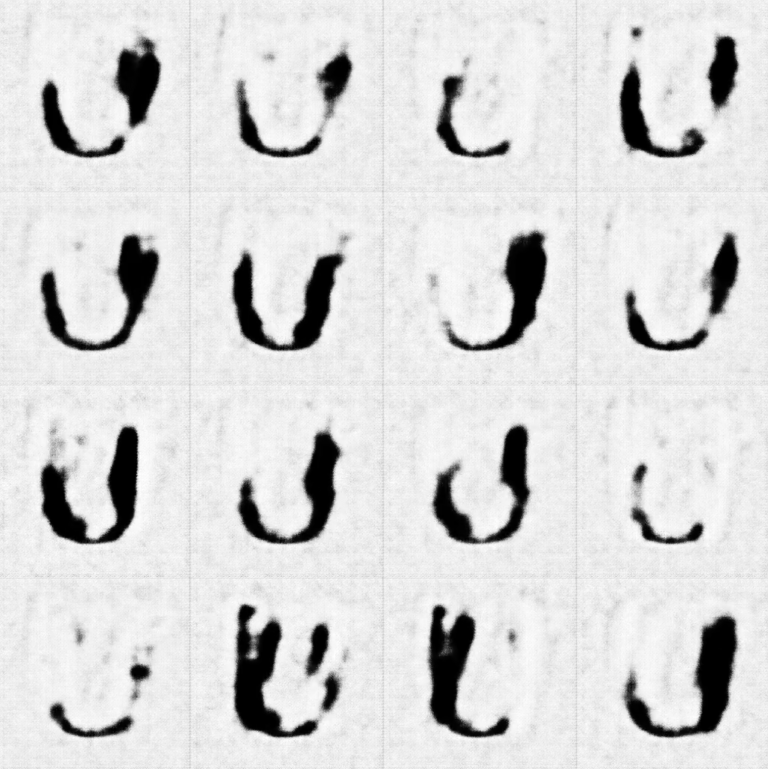
Relevancia
Aifont es un sistema de identidad visual generativa desarrollado para la exposición Uncanny Values en la Bienal de Viena. El proyecto utiliza redes generativas antagónicas (GAN) para procesar un conjunto masivo de fuentes y emojis, generando nuevos glifos que oscilan continuamente entre diferentes pesos y estilos.
Su principal aportación es la materialización del aprendizaje no supervisado como proceso de diseño. En lugar de definir reglas fijas, el sistema imita el proceso cognitivo de aprender a escribir, produciendo formas que resultan familiares pero inquietantes, visualizando estéticamente la incertidumbre de la inteligencia artificial.
La relevancia de este proyecto es que aporta un referente clave sobre cómo la inteligencia artificial puede actuar como cocreadora de una identidad visual dinámica a través de la tipografía generativa.
Clasificación
- Década: Década de 2010
- Función: Exploración formal y/o performativa
- Contexto: Branding
- Institución: Mak Museum
- Grado de interactividad: Interacción generativa
- Input multimodal: No
- Tipo de input: Algoritmo
- Tipo de output: Generación tipográfica
- Tecnología empleada: GAN (Generative Adversarial Network)
- Alfanumérica: Sí
- Mantiene codificación textual: No